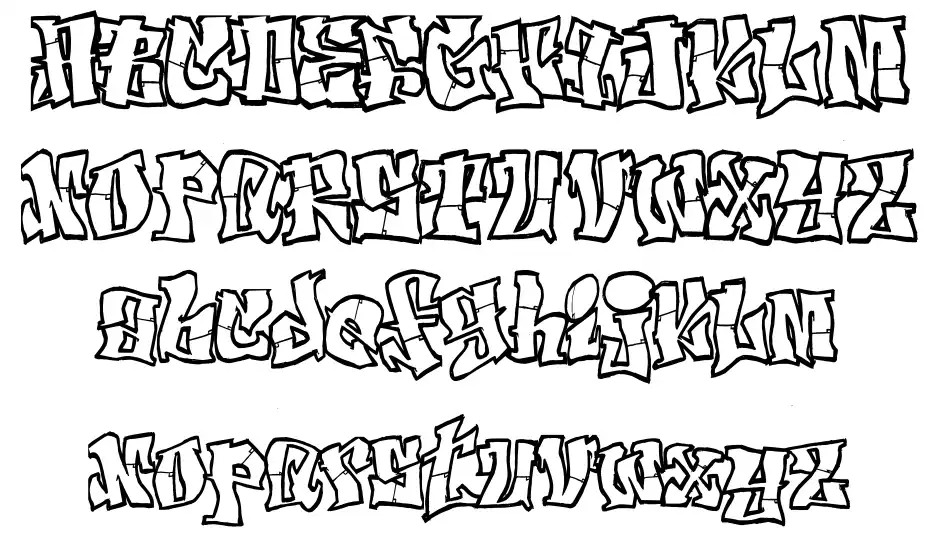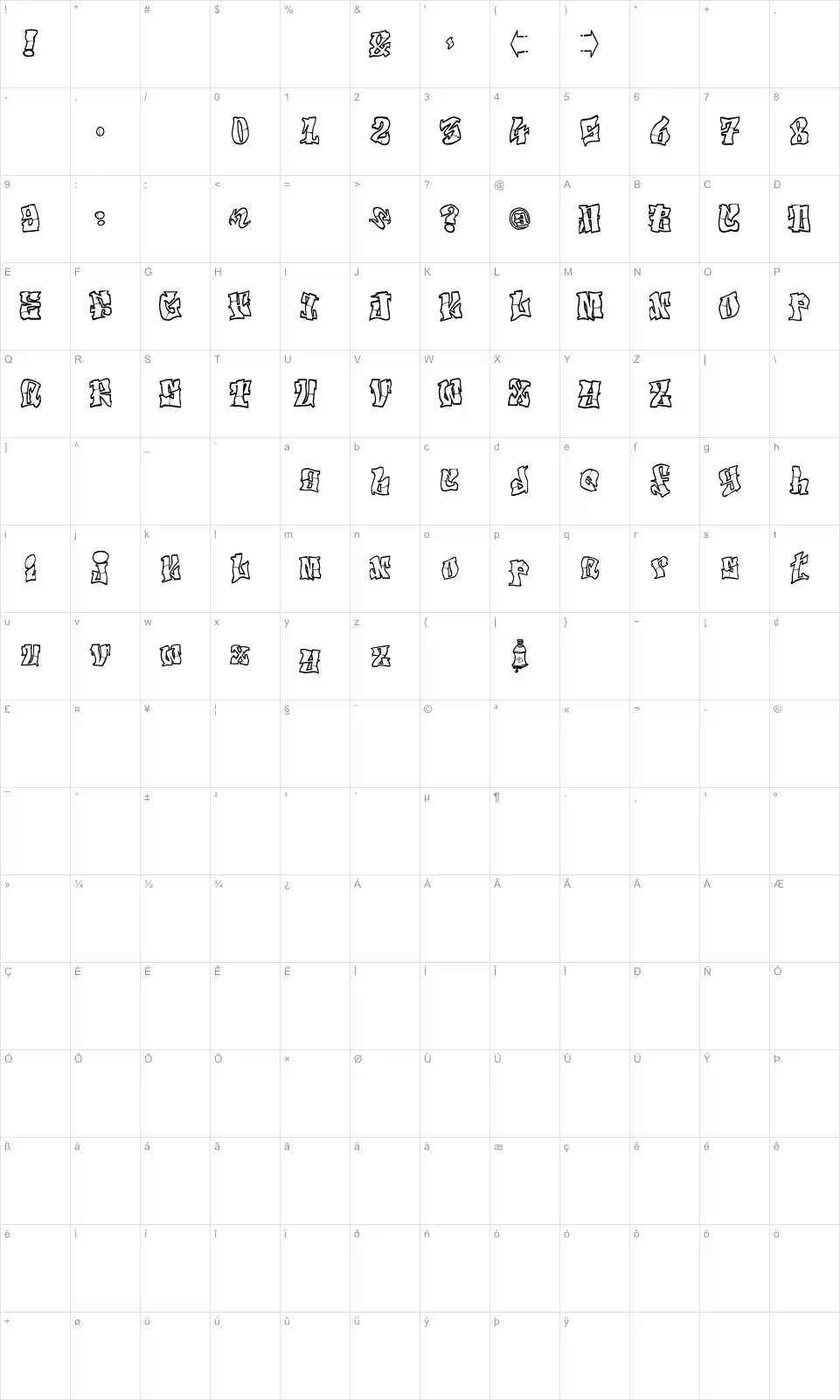
A fonte El&Font Tag! é uma opção moderna e criativa para aqueles que desejam adicionar um touch único ao seu design, especialmente em contextos pessoais. Criada pelo designer Jérôme Delage, esta fonte Script é ideal para adicionar um gosto graffiti ao seu material. Com sua licença gratuita para uso pessoal, você pode experimentar a fonte facilmente sem preocupações legais. Esta fonte foi adicionada ao nosso catálogo em 12 de julho de 2022, já tendo sido baixada mais de 46.759 vezes. Com um tamanho de 64 KB, El&Font Tag! é compacta e fácil de integrar em qualquer projeto. Se você está procurando por uma fonte que combine elegância com originalidade, El&Font Tag! poderia ser perfeito para você. Experimente a fonte online e veja como ela se destaca em seu próximo projeto.
Categoria: Script › Graffiti
Designer: Jérôme Delage